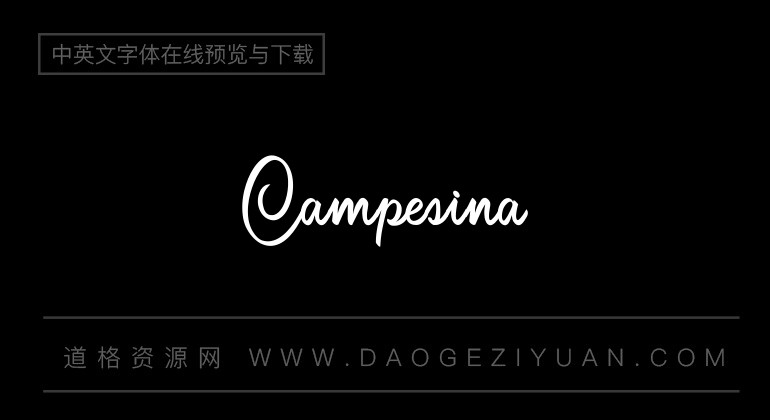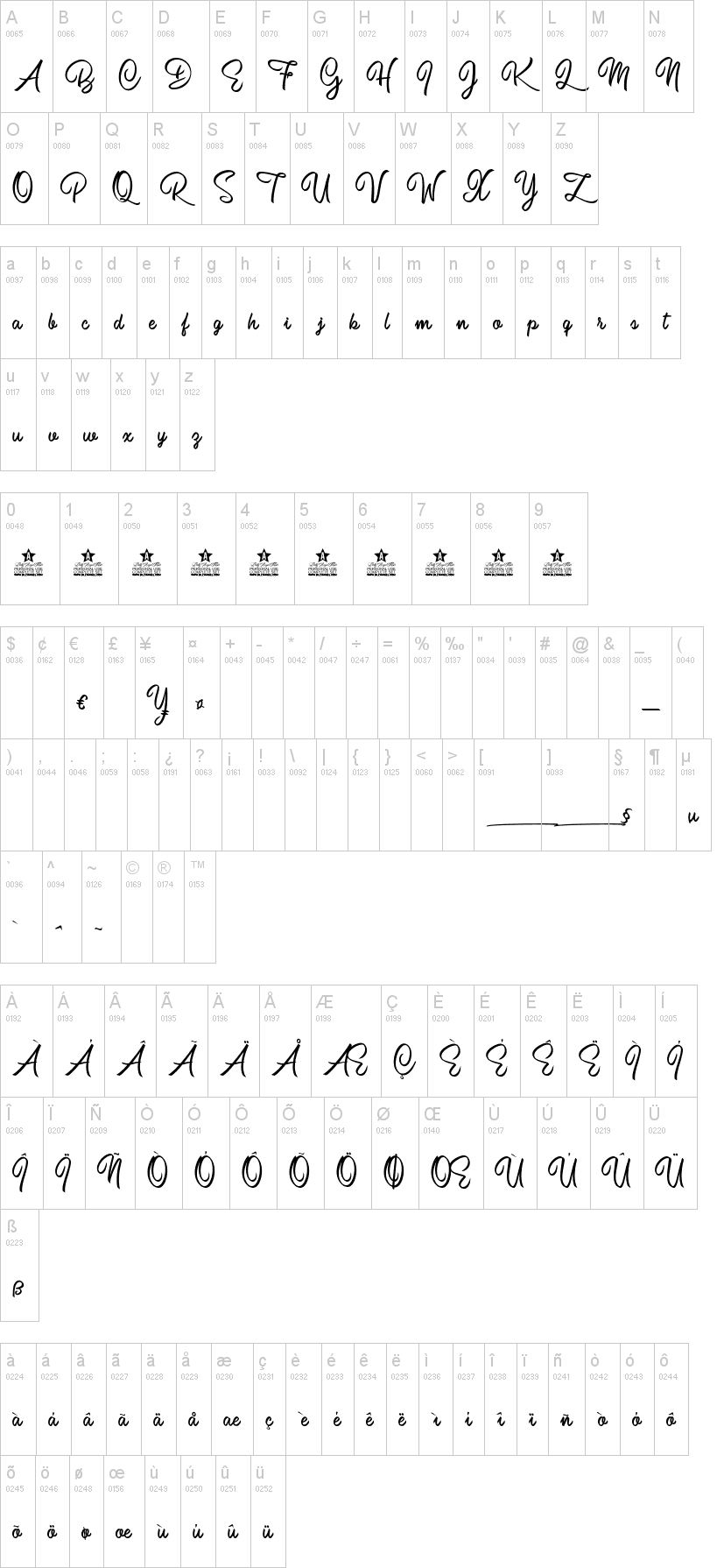
Campesina
Campesina 是一种专为西班牙语设计的粗体字体,由西班牙设计师Juanjo López de la Cruz于2015年设计。它有着粗体、深色的外观,具有极具表现力的西班牙语字体,非常适合用于标题、广告、封面等场景。Campesina 的设计特点是深色的字体,具有较高的对比度,可以在复杂的环境中脱颖而出。同时,它还具有较强的可读性,可以更好地表达文字内容。
Campesina是一款非常不错的手写艺术字体,具有很好的视觉感,适合于文化类的宣传设计、商业类品牌的广告和产品包装设计以及个性化文字排版等较多场景。